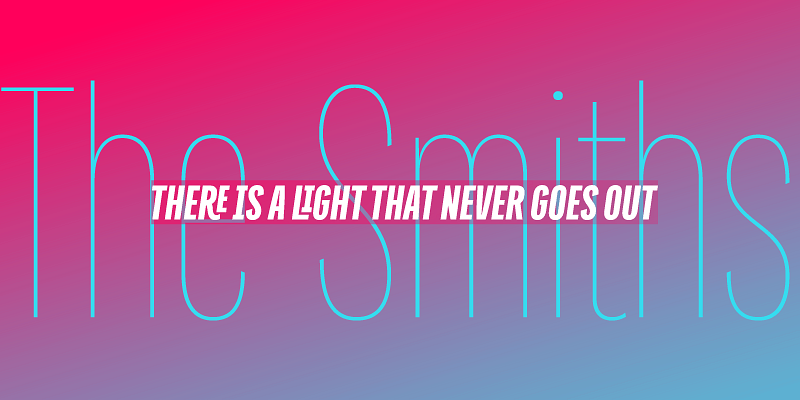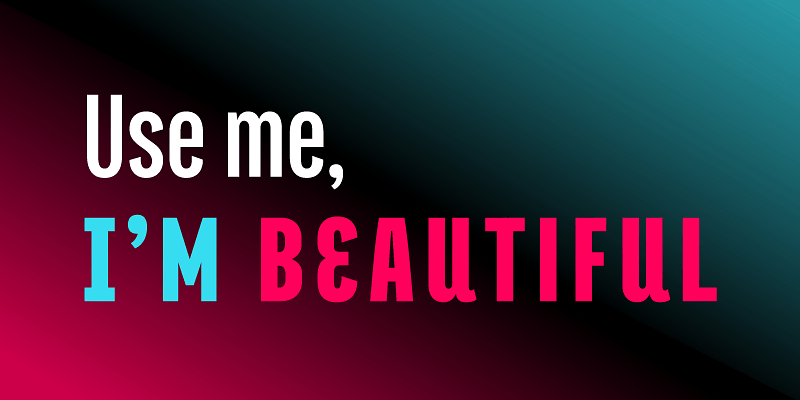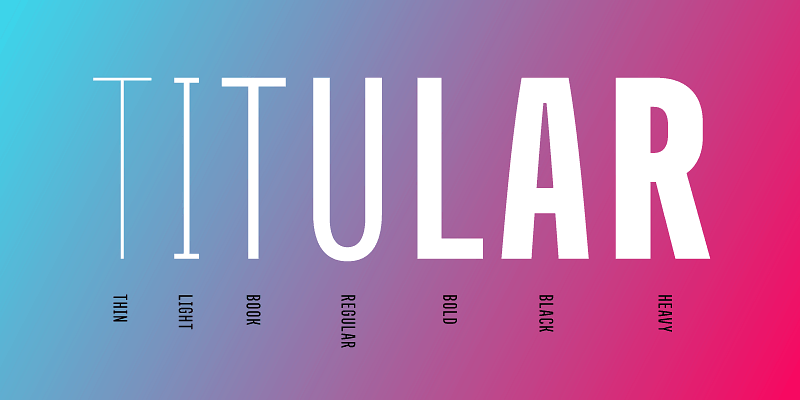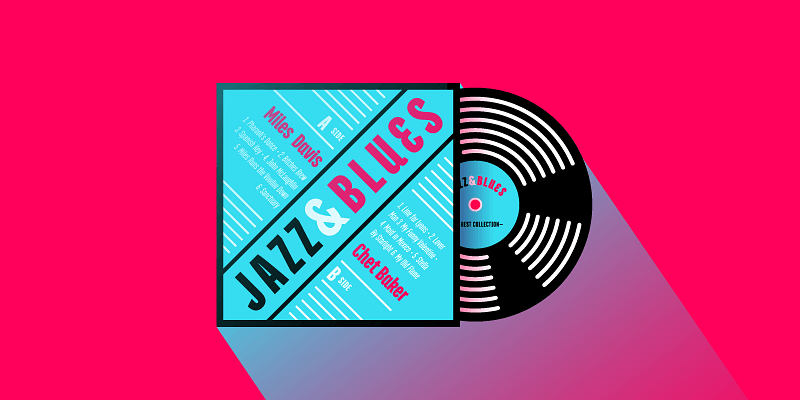
Titular ist eine kondensierte serifenlose Schrift, die sich gut für Überschriften, Zwischenüberschriften, Zeitungen, Zeitschriften sowie für Logotypen, Marken und Plakate eignet.